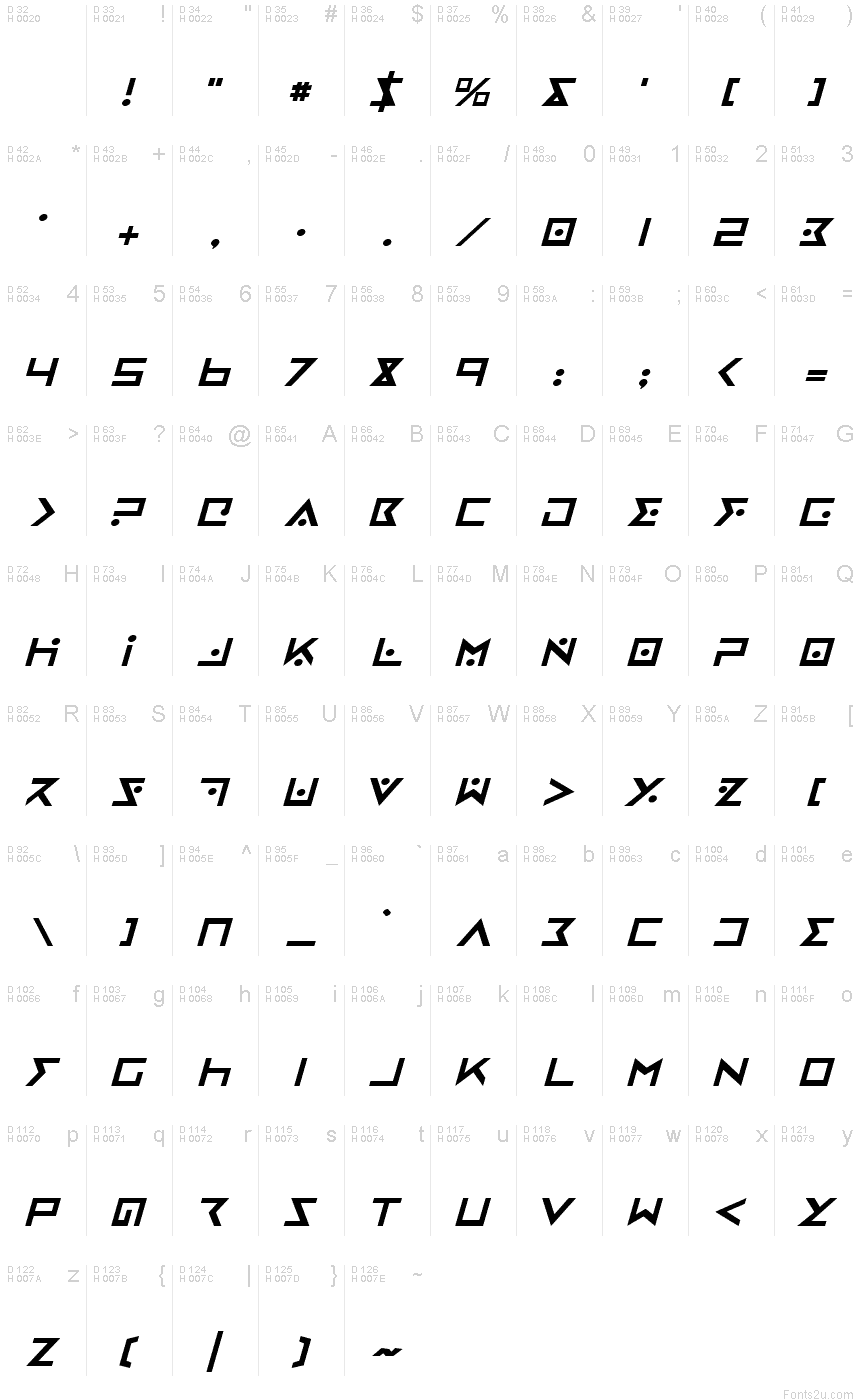
Iron Cobra Italic, darmowy futurystyczny krój techniczny typu display od Iconian Fonts, pędzi przed siebie dzięki stromemu pochyleniu i ostro wyciętym, geometrycznym formom. Od premiery w 2008 roku łączy szerokie, kanciaste pociągnięcia z otwartymi, „ciętymi” kształtami, które przywodzą na myśl grafikę wyścigową i sprzęt science-fiction.
Napięte kąty budują wrażenie szybkości i mechanicznego napięcia w brandingu esportowym, tytułach gier i plakatach sportów motorowych. Wykorzystaj ten darmowy font w projektach opakowań sci-fi, materiałach promocyjnych dla muzyki elektronicznej czy bannerach interfejsów, gdzie jego wyrazista sylwetka może współgrać z metalicznymi motywami, efektami ruchu i dynamicznymi kompozycjami.